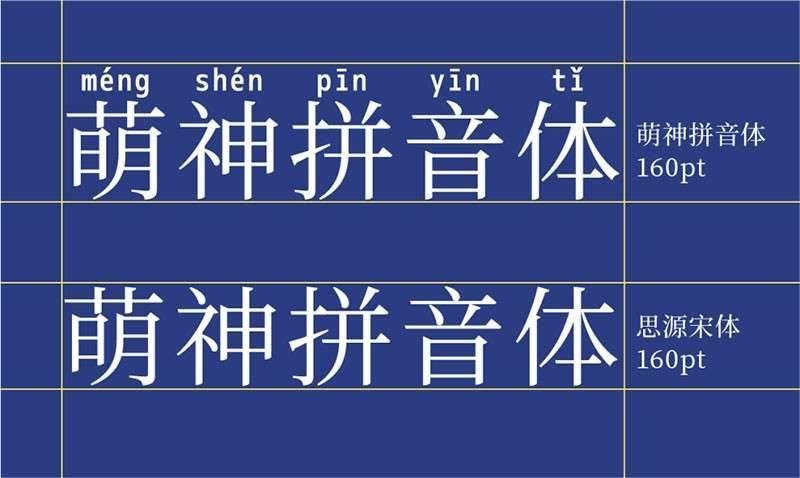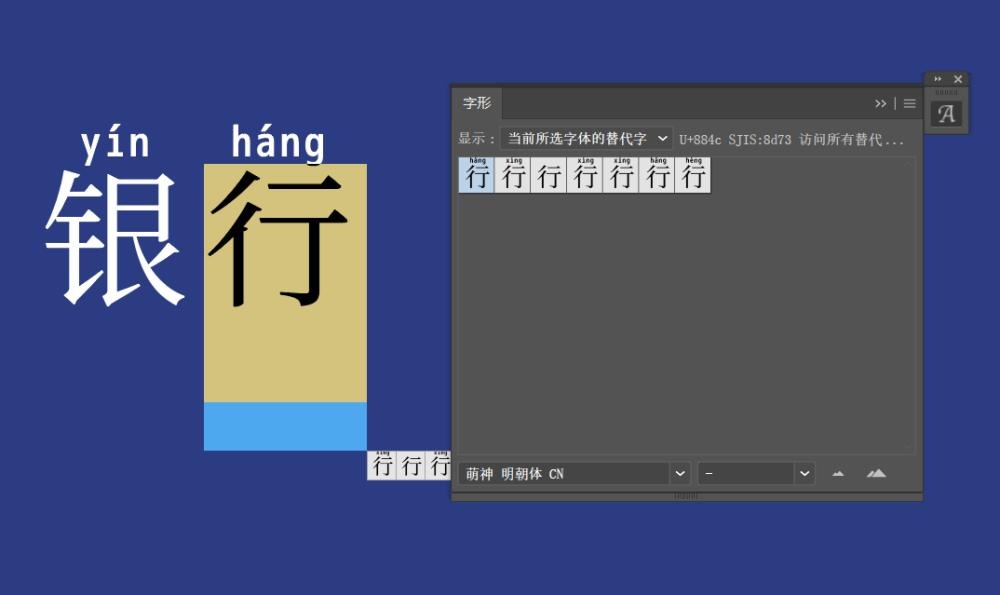
萌神拼音体(Mengshen Pinyin Font)是由日本 MaruTama(Geek 中文学会)基于思源宋体 和 M+ 字体改造而成的一款免费可商用开源中文字体。
字体主要面向中文、日语学习爱好者,主打一个汉音同步。在输入汉字时,文字上方会自动生成标准普通话拼音(含声调)。而且还支持多音字智能识别,比如(银行 → yín háng)和(行走 → xíng zǒu)可以根据语境自动识别,无需手动矫正和排版,非常适合汉语初学者、儿童识字教育、汉语教学等场景。
萌神拼音体兼容简体字、繁体字、日语汉字、平假名和片假名。有宋体(萌神拼音体)和手写体(萌神手写体)两种风格,前者工整清晰,适合正式场景;后者萌动可爱,适合文创艺术类用字。